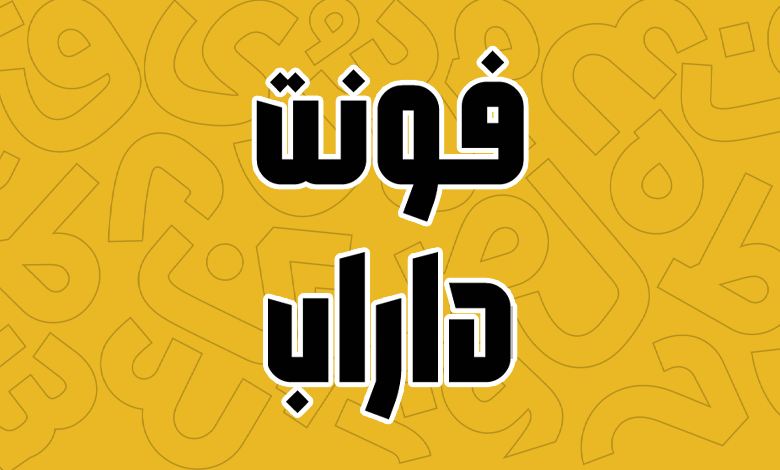
فونت داراب (Darab)
فونت داراب (Darab) قلمی در گروه عنوان و مناسب تبلیغات است که با توجه به ساختار هندسی خود در گروه فونتهای فشرده قرار میگیرد. این فونت حاصل جنبو جوش و تکاپوی زوایای قائم است که ساختار این فونت را تشکیل داده و مانند فونت آرتین فاقد زوایا و منحنی در بخش قائمه حروف است.
فونت داراب توسط امیرارسلان احمدی طراحی شده و شهرزاد اکبری این فونت مناسب عنوان را که در حوزه چاپ و تبلیغات، بهخصوص برای طراحی انواع پوستر کاربردی است به فرمت فونت نرمافزاری تبدیل کرده است.
در ادامه این نوشته از سایت فونتچی به نقد و بررسی کامل فونت داراب خواهیم پرداخت؛ قلمی که جزو معدود فونتهای با قابلیت تنظیم ارتفاع بوده و ساختار آن بر اساس خطوط قائم تشکیل شده است.
با اینکه فونت داراب یک فونت قائم بهنظر میرید که در منحنی حروف فاقد زوایا بوده و قلم متناسب با چرخش حروف با همان پهنا تغییر میکند، اما ساختاری مدن داشته و ضمن اینکه ایستا به نظر میرسد، رفتار آن با توجه به قابلیت تنظیم ارتفاع و فشردهسازی که از طریق آن در اختیار قرار میدهد کاملا پویا است.
سبک طراحی و وزن فونت داراب
داراب فونتی کاملا هندسی است که با تاکید روی محور عمودی و پر کردن فضای منفی حروف ساخته شده است. بههمین جهت دارای ساختاری کاملا عمود است که در نسخه وریبل امکان تنظیم ارتفاع متناسب با نیاز جدایی از قابلیت تنظیم وزن درون آن گنجانده شده است.
این فونت که دارای ۴ وزن Regular، Medium، DemiBold و Bold است، امکان تغییر ارتفاع حروف را در ۳ ارتفاع نیز خواهد داد. در نتیجه با فونتی سر و کار داریم که در مجموع امکان تایپ حروف را در قالب ۱۲ سبک با وزنهای مختلف در اختیارمان قرار خواهد داد.
پشتیبانی از ۵ زبان مختلف
فونت فارسی داراب محدود به این زبان نبوده و از ۴ زبان مختلف دیگر که بر اساس رسم خط فارسی و لاتین هستند نیز پشتیبانی کاملی دارد. با توجه به یکسان بودن این حروف در دو دستهبندی زبان، میتوان انتظار استفاده از آن را در سایر زبانها را هم داشت؛ اما بدینصورت که پشتیبانی از سایر زبانها کامل نبوده و فاقد برخی ترکیبات و گلیفها است.
در زبان عربی کلیه حروف فارسی به انضمام حروف عربی مثل «ک، ی، ه، ؤ، ئ» که تقاوت جزئی دارند جای داده شده است. همچنین کلیه اعراب این زبان نسخه عربی به شکل استاندارد درج شده است. برای مثال اعرابی که همراه با تشدید در حروف باشند، در کنار تشدید قرار میگیرند تا ساختار کلمات بههم خورده نبوده و درستنویسی رعایت شده باشد.
زبان کردی و اردو هم که بر اساس همین رسم خط فارسی هستند در این قلم پشتیبانی شده و همراه با اعراب و گلیفهای تزئینی است که به وفور روی حروف مختلف از آنها استفاده میشود.
در فونت انگلیسی داراب شاهد پیادهسازی همان مدل طراحی خطوط قائم هستیم که برای هماهنگی با حروف فارسی به صورت اختصاصی طراحی شده است. همچنین اعداد در حروف لاتین به شکل اختصاصی طراحی شده است.
در نسخه لاتین این فونت امکان تایپ برای زبانهای غیر انگلیسی نظیر ترکی استانبولی و فرانسه نیز فراهم است؛ اما یک ایراد جزئی که وجود دارد این است که در برخی ترکیبات حروفی مثل «ı, ğ, ç, ü» که در این زبانها ساختاری متفاوت دارند درست تایپ نشده و از ساختار این فونت پیروی نمیکنند که انتظار میرود این مسئله نیز در نسخههای آتی رفع شود تا امکان استفاده از این فونت برای زبانهای ترکی استانبولی و سایر زبانهای لاتین نیز فراهم شود.
دارای حروف و ترکیبات جایگزین متنوع
فونت داراب دارای ترکیبات حروف متنوعی است که امکان تایپ متفاوت برخی کلمات کلیدی درون محتوا را به شما خواهد داد. به کمک این ویژگی میتوانید حروفی که از تایپ متفاوت پشتیبانی میکنند را بسته به نیاز خود در چند مدل مختلف تایپ کنید که شکل کلی جملهبندی را تغییر داده و زمانی که در کلمات مهم مورد استفاده قرار گیرند؛ خصوصا با هدف تبلیغات، میتواند موجب جلب توجه بیشتر شود.
برای نمونه همانطور که در تصویر متحرک زیر میبینید، حروف و ترکیبات «ـگ، ت، ن، هـ، ـه» دارای شکل متفاوتی برای تایپ هستند و بسته به اینکه در ابتدا، انتها یا میانه کلمات باشند امکان تایپ در چند ظاهر مختلف را به شما خواهند داد.
یا در نمونه دیگری مشابه تصویر متحرک پایین برای تایپ حروف «ه، ی» در میانه یا انتهای کلمات میتوانید از دو یا چند ترکیب مختلف استفاده کنید.
ترکیبات جایگزین فونت داراب محدود به این عبارات نبوده و در سایر حروف مثل «س، ش، ص، ض» نیز امکان استفاده از این ترکیبات را دارد. در بسته راهنمای دانلود فونت داراب تمامی لیست این حروف جایگزین همراه با شورت کدها و روش استفاده از آنها در OpenType نرمافزارهای گرافیکی و محیط وب برای فرمتهای WOFF درج شده است که میتوانید از آنها کمک بگیرید.
دارای اعداد فارسی هک شده و اعراب هر زبان
اعداد در فونت داراب از دو ساختار پشتیبانی میکنند که در بسته دانلود قلم داراب نیز روی این مسئله تاکید شده است. یعنی پوشهای مخصوص اعداد فارسی وجود دارد که با نام FarsiDigits یا به اختصار FD نام فونتها تعیین شده است.
این گروه از فونتهای داراب دارای اعداد هک شده فارسی هستند. یعنی زمانی که صفحه کلید شما روی زبان غیر لاتین قرار دارد یا اینکه از بخش صفحه کلید اعداد استفاده میکنید، هرچند که اعداد را انگلیسی تایپ میکنید اما به صورت فارسی تایپ خواهند شد. دلیل آن هم جایگزینی گلیف اعداد فارسی در نسخه لاتین است.
جدایی از این فونت داراب برای اعداد زبان عربی «۴۵۶» از همان ساختار استاندارد این زبان پشتیبانی میکند و این اعداد زمانی که صفحه کلید روی نسخه عربی باشد، به جای «۴۵۶» فارسی با همان ساختار عربی تایپ خواهند شد.